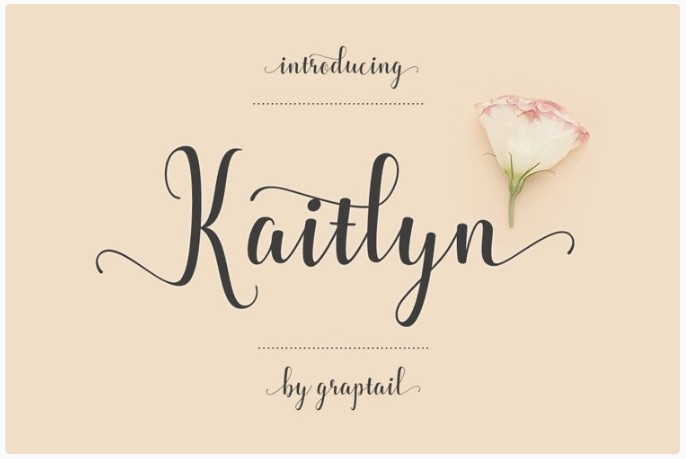
Fontbundles Kaitlyn Font 2021
[Fontbundles] Kaitlyn Font (2021)
Kaitlyn Script - современный шрифт, каждая буква которого тщательно проработана, чтобы ваш текст выглядел красиво.
Этот шрифт идеально подходит для различных проектов, например: цитаты, заголовки блогов, плакаты, свадьбы, брендинг, логотипы, мода, одежда, письма, приглашения, канцелярские принадлежности и т.д.Kaitlyn Script включает альтернативные глифы. Доступ к нему возможен с помощью программ, поддерживающих OpenType, таких как Adobe Illustrator и Adobe InDesign.